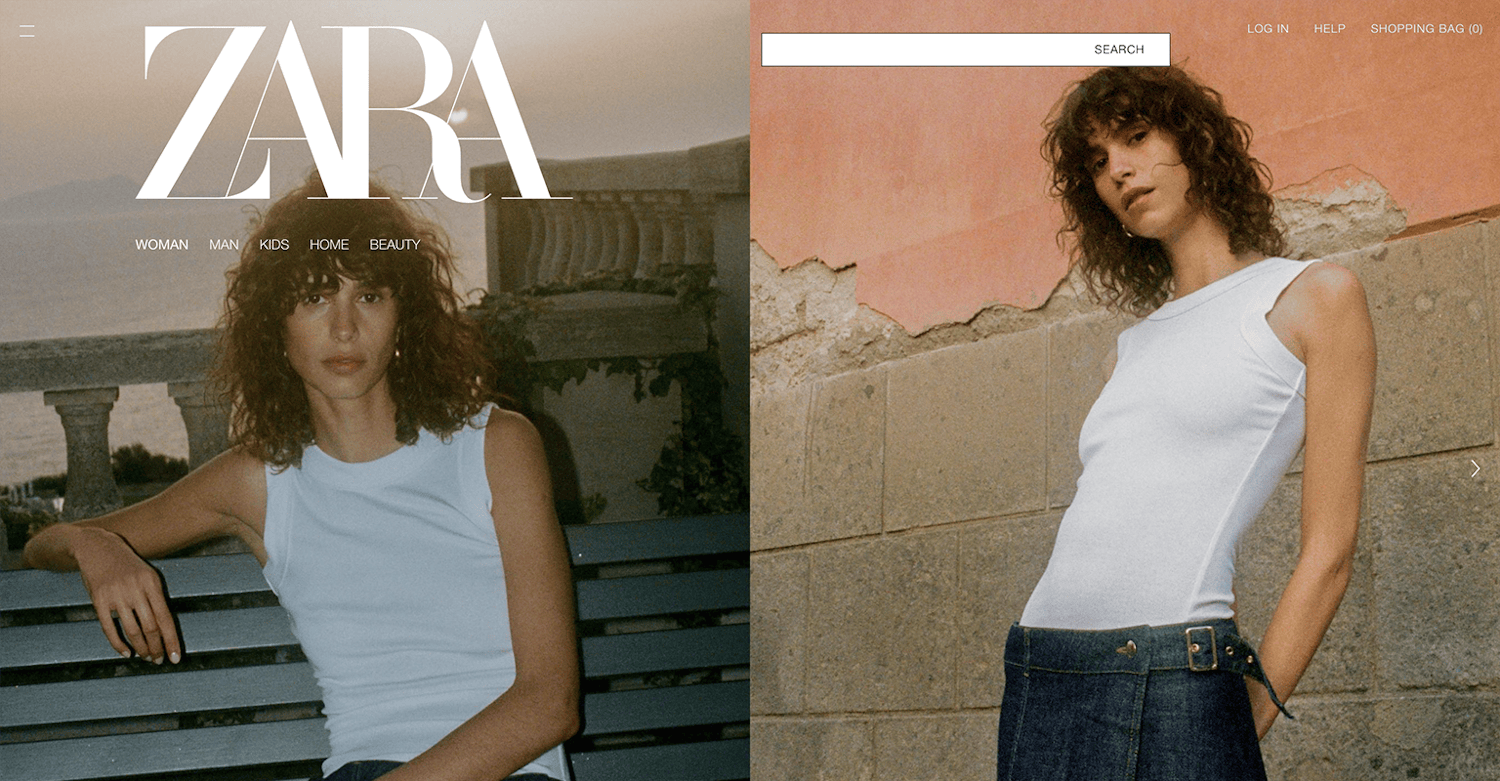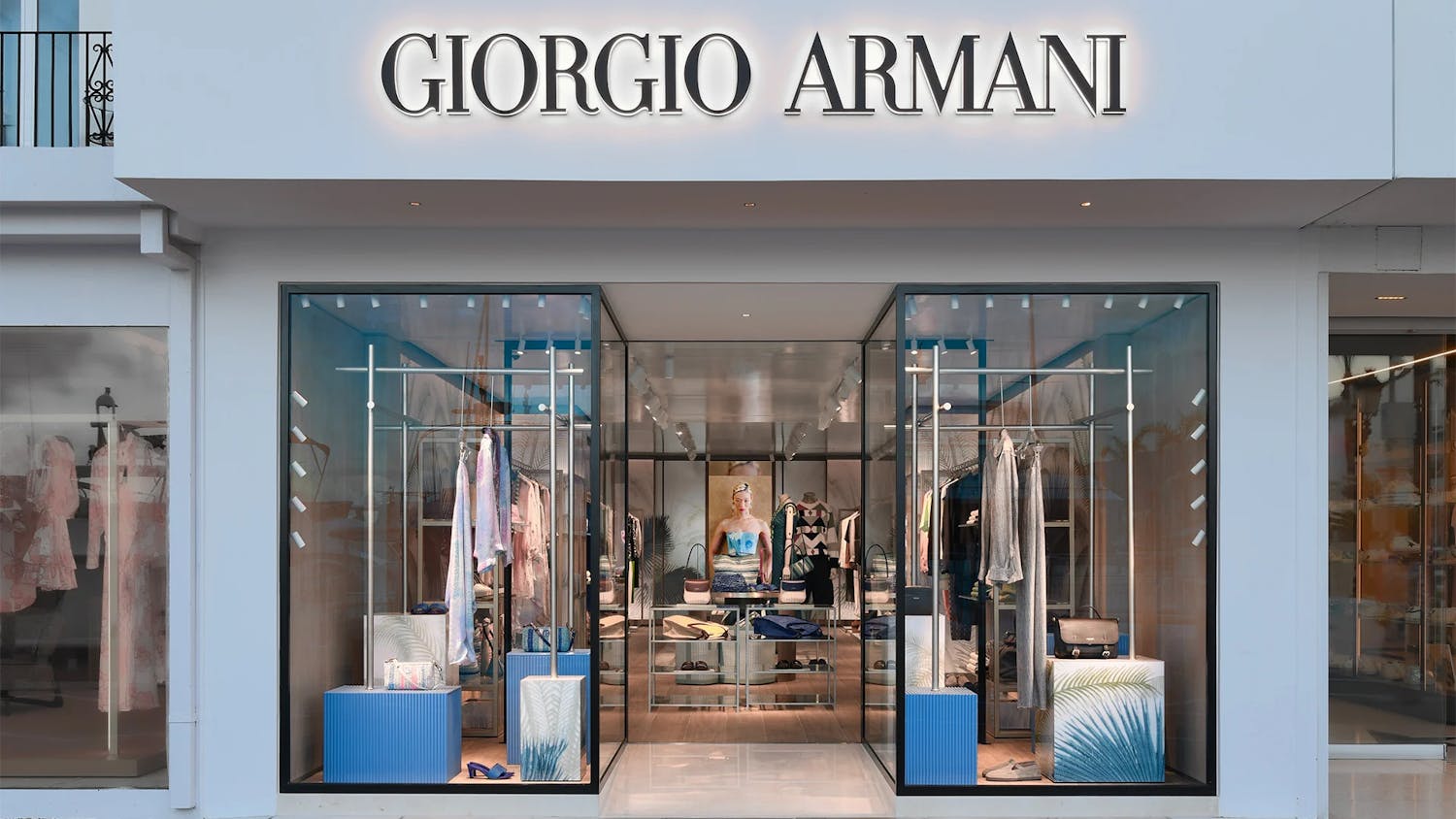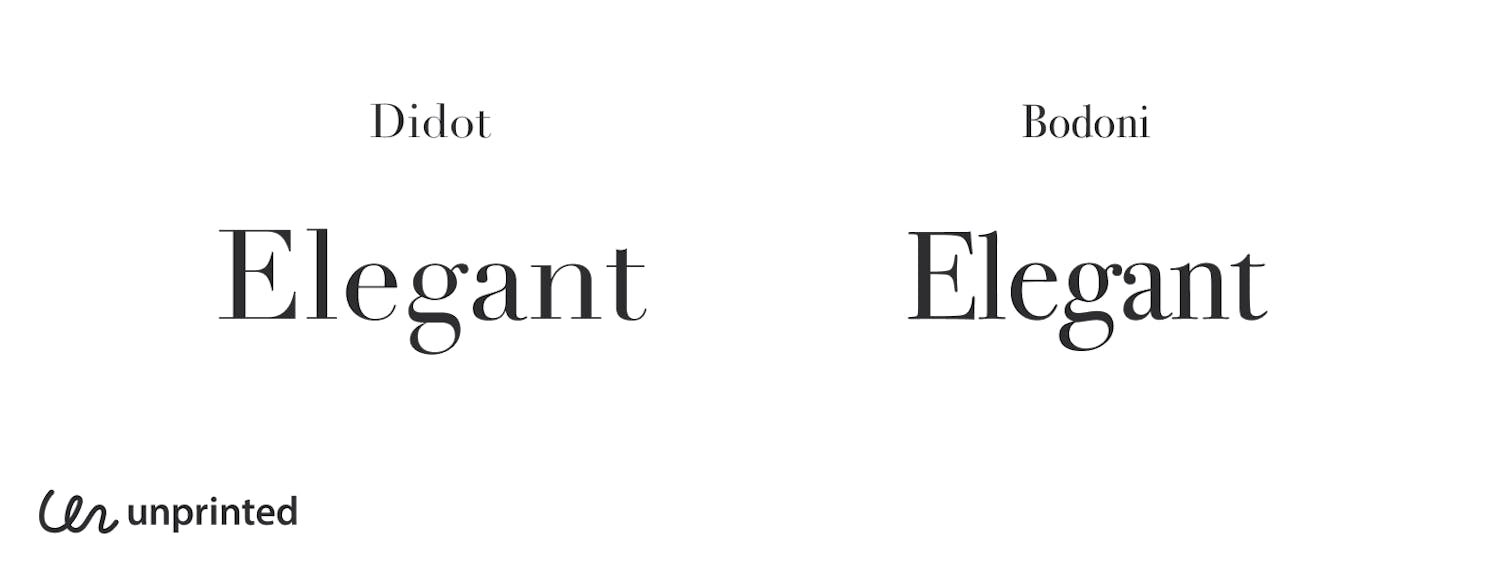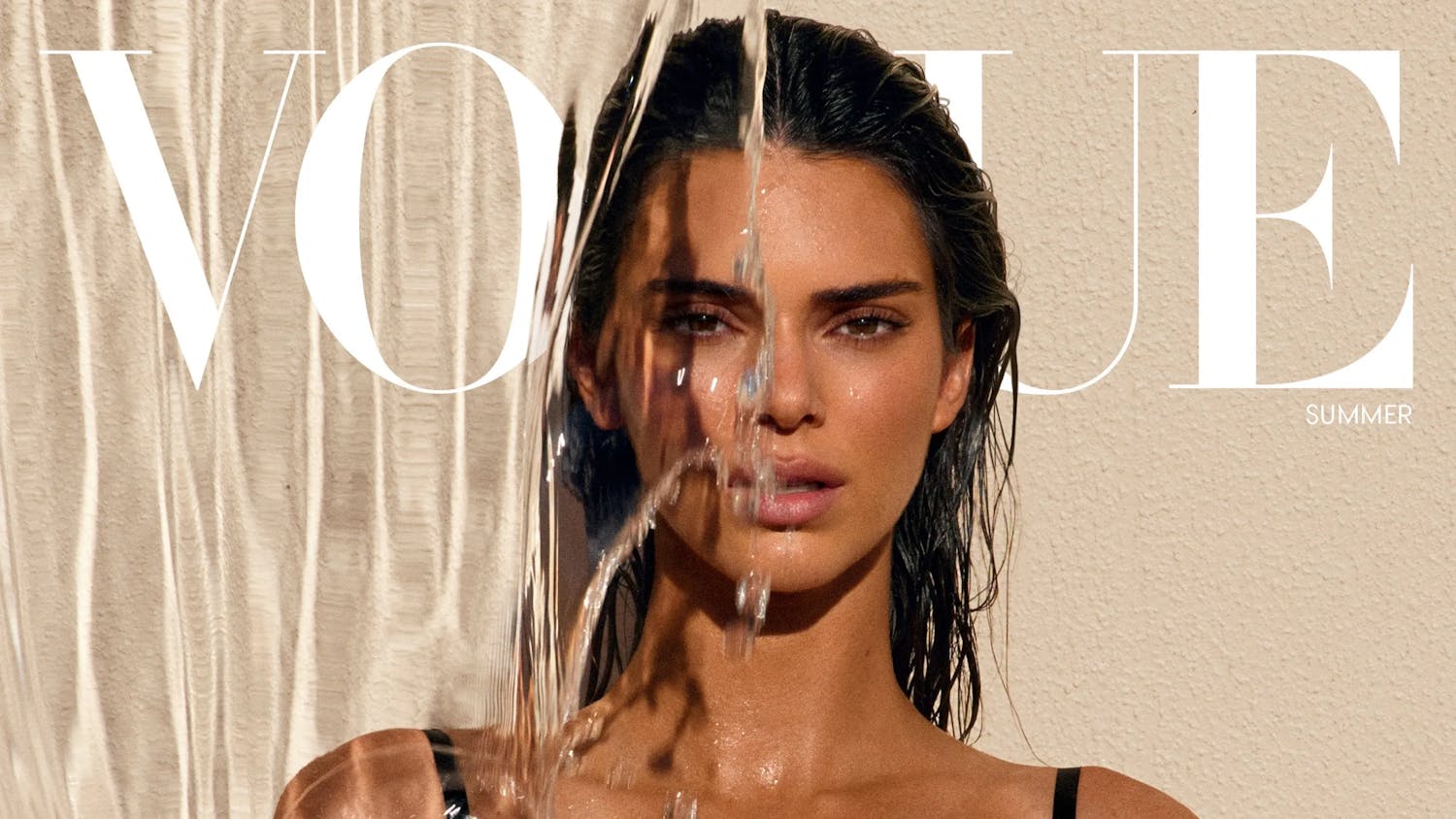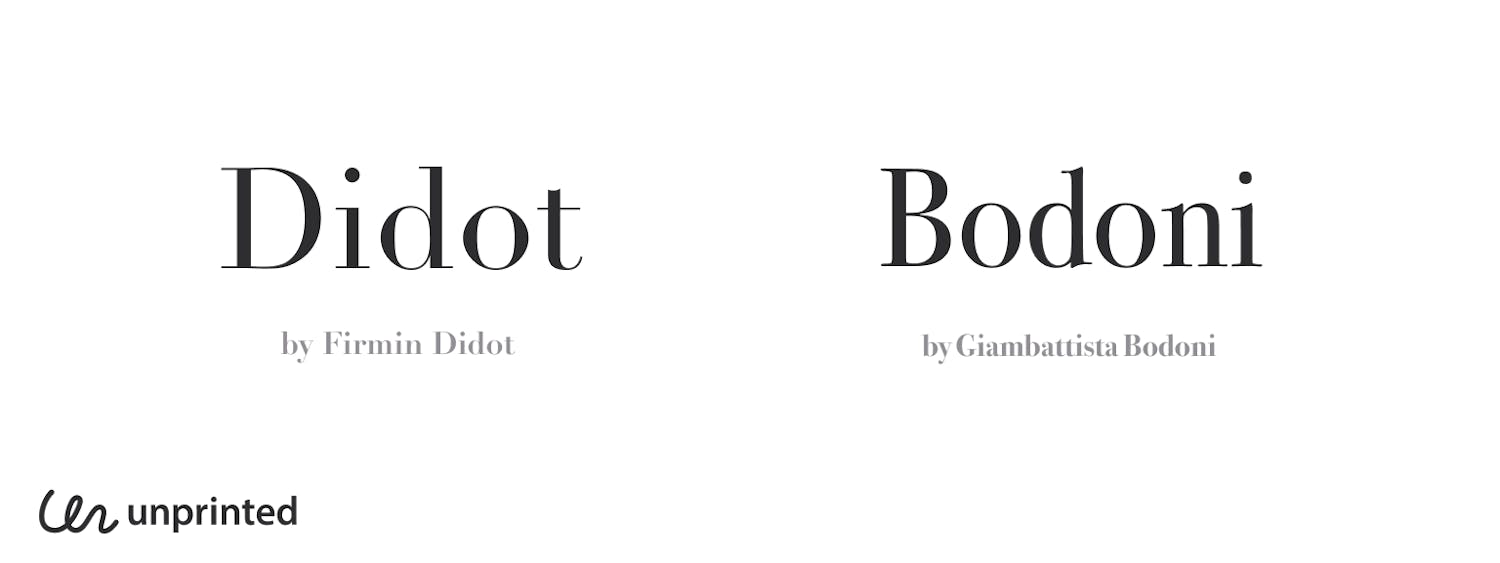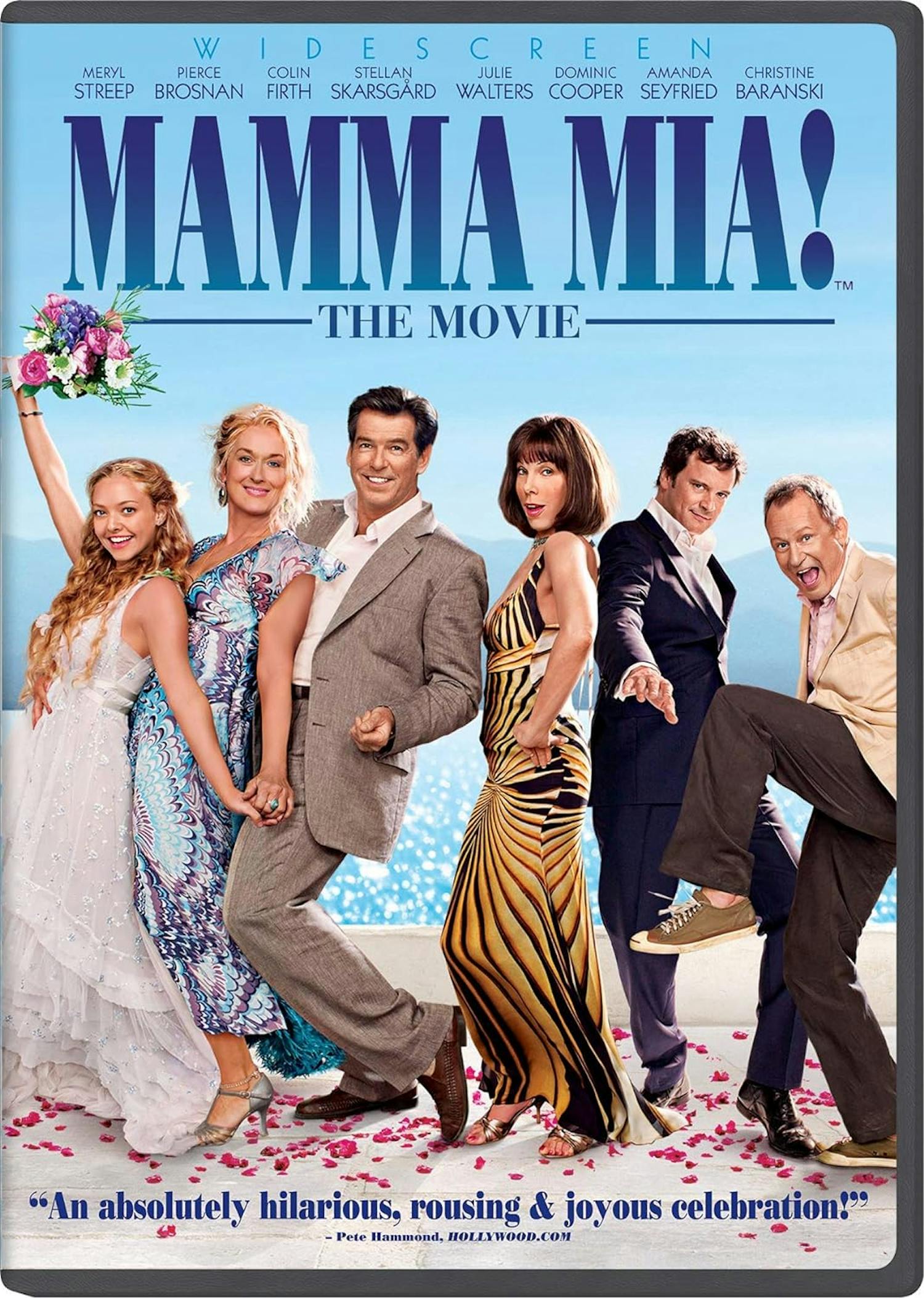
ラグジュアリーな書体の代表格『Didot』と『Bodoni』の使い分け
ファッション誌やハイブランドのロゴとしてよく使用されていることから、高級でおしゃれなイメージがある書体「Didot(ディド)」と「Bodoni(ボドニ)」について、その成り立ちや使い分けに役立ちそうなポイントを紹介します。
同時代に生まれたDidotとBodoniのコンセプト
一見するとデザインが似ているDidotとBodoniですが、それは制作された時代背景と、表現したいコンセプトが同じであったことが理由であると考えられます。Didotはフランスで、印刷業で働いていたFirmin Didot(フェルミン・ディド)によって、Bodoniはイタリアで、こちらも印刷業かつ書体デザイナーであったGiambattista Bodoni(ジャンバッティスタ・ボドニ)によって制作されました。どちらも18世紀後半から19世紀初めに生まれた書体で、その背景には産業革命による工業の発展があります。向上した印刷技術や製紙技術によって、より精密なラインやコントラストを備えたデザインの表現が可能になったのです。制作者のディドとボドニが目指したのは、技術の向上を誇示するような、よりエレガントで洗練された書体デザインをこれからの印刷の標準スタイルとすることでした。
Didoneという書体ジャンル
Didone
両書体が生まれた18世紀後半から19世紀初めに制作され、印刷の標準スタイルとなったセリフ体をまとめて「Didone(ディドネ)」と呼ぶことがあります。以下の特徴を持った書体が、Didone書体として分類されます。
• 細い直線による、ヘアラインセリフを持つ
• 線の太さにコントラストがあり、縦線が太く、横線が細い
• いくつかの文字で、先が丸いボール上のターミナル(終端)が使われている
• 飾りがない、”モダン”な見た目
特に4番目の特徴は、現代でもDidotとBodoniが好まれて色々な場所で使用される理由と言えそうです。エレガントでありながら書体の細かい構成要素がシンプルに作られていることで、存在感がありながら、様々なジャンルで相性良く溶け込ませることができます。
ディド家が確立させた書体のポイントシステム
ここで本題から少し話が逸れますが、Didotを制作したフェルミン・ディドの一族が確立した、書体のポイントシステムについて触れます。現代で当たり前のように使用されている書体のサイズを測るための単位「ポイント(例:16pt)」ですが、このシステムの開発に深く関わっているのがディド家であり、タイポグラフィの発展に大きく貢献したことで知られているのです。それまで書体のサイズについては決まった単位がなく、特定のサイズの書体に固有名詞(例:12pt= picaなど)を当てはめて呼ぶということが一般的でした。ディド家は、それより前に開発が進められていたフルニエ式をより実用的なものに修正し、ヨーロッパで標準単位として使用されることになるディド式ポイントシステムを確立させました。ちなみに日本では、規格が違うアメリカ式ポイントシステムを採用しています。
DidotとBodoniはどのように使い分ける?
このように、DidotとBodoniは様々な点から似ている書体ということが改めてわかりました。どちらも美しい書体ですが、細かく見てみるとそのデザインにはしっかりとした違いがあり、表現したいイメージよって使い分けすることができそうです。
DidotとBodoniはどのように使い分ける?
同じテキストを2つの書体で書いて比べてみると、Didotは”○(丸)”の中に、Bodoniは”□(四角)”の中に収まりが良さそうと思いませんか?曲線により丸みがあるDidotは女性的な柔らかさがあり、Bodoniはシュッと伸びた太い縦線が特徴的で、男性的なかっちりした印象があります。このような印象の違いから、より直線の太さが目立ち重厚感のあるBodoniは格式ある場所に、曲線が美しく動きのあるDidotは高級感と同時にカジュアルさを表現したい時に、などデザインの意図に合わせて使用していきたいですね。
Didotはファッションブランド御用達の定番書体
Didotはロゴとしても良く採用されていますが、特にハイブランドをはじめファッション業界で好まれている書体で、皆さんも雑誌やお店のロゴでDidotをベースにしたものを目にしたことがあるかもしれません。細い線から感じられる繊細さとセリフのエレガントさがあるDidotを、ファッション業界で使用したくなるのは納得です。
雑誌「VOGUE」のロゴ
雑誌「VOGUE」のロゴ(https://www.vogue.com/magazine)
ファッションブランド「ZARA」のロゴ
ファッションブランド「ZARA」のロゴ(https://www.zara.com/jp/en/)
ファッションブランド「Giorgio Armani」のロゴ
ファッションブランド「Giorgio Armani」のロゴ(https://www.armani.com/en-us)
Bodoniはファッションや芸術分野で幅広く、特にタイトル向け
Bodoniについても、Didotと同様にファッション関連のブランドのロゴとしてよく使用されています。また、Bodoniは縦線の太さがより際立ち強い印象を残すことが期待できるので、このことから映画のポスターのタイトルなど、タイポグラフィのメインとなる場所で使用されているのも発見できます。
映画「マンマ・ミーア!」のタイトルロゴ
映画「マンマ・ミーア!」のタイトルロゴ(https://www.amazon.com/Mamma-Movie-Widescreen-Meryl-Streep/dp/B001GKJ2DY)
DidotとBodoniをデジタル環境で使用するには?
DidotとBodoniは長い歴史がある書体なので、これまで様々な種類がリリースされています。Didotについては、アドリアン・フルティガーが1991年にオリジナルをもとにデザインしデジタル書体としてリリースされた「Linotype Didot」が、Adobe Fontsからもアクティベートできるのでおすすめです。
Bodoniのデジタル書体は複数種類あり、オリジナルに近づけたものからかけ離れたものまで本当に様々です。macOSに標準インストールされている「Bodoni 72」は馴染みがある方も多いですよね。こちらのフォントは名前の通り”72pt”での使用が想定された見出し向けのフォントであり、小さいサイズで使用する場合は他の種類の方が適していたりします。Bodoniについては、その時の使用場所やコンセプトに合わせて種類を検討するのが良さそうです。オリジナルからかけ離れたデザインでも、それが悪いということではなく、デジタル向けに最適化されたことでセリフがシンプルになっていたり線のコントラストが調整されている、という違いが含まれます。好みのBodoniを見つけてみるのも面白そうですね。
まとめ
ここまで、セリフ体として長い歴史があるDidotとBodoniについて紹介しました。Didone書体と呼ばれるこれらの書体は、目にした人みんなが”ラグジュアリーさ”と”エレガントさ”を感じ取る、イメージが確立された書体と言えます。そのようなタイポグラフィを表現したい時の第一の選択肢としてデザインの引き出しに入れておきたいですね。